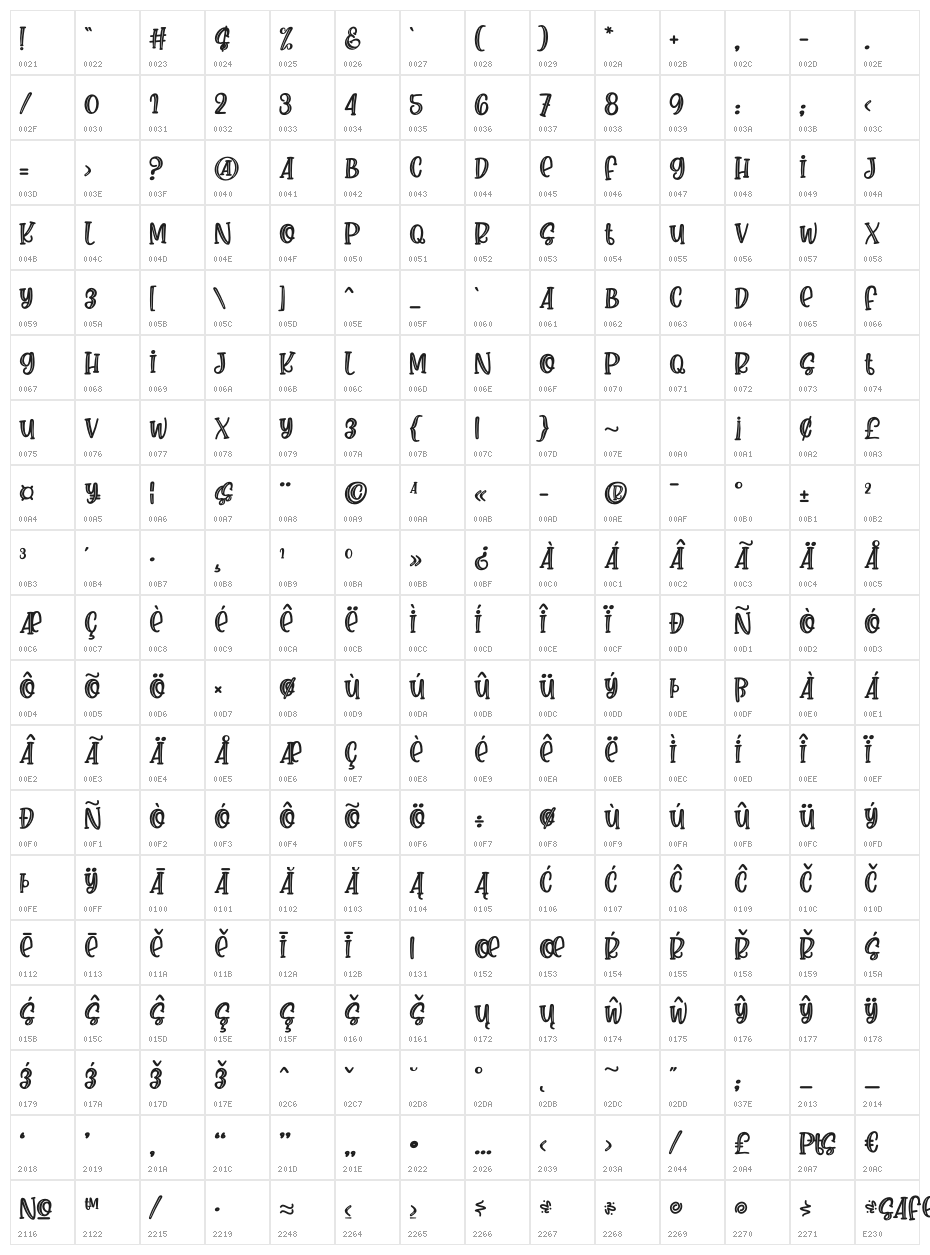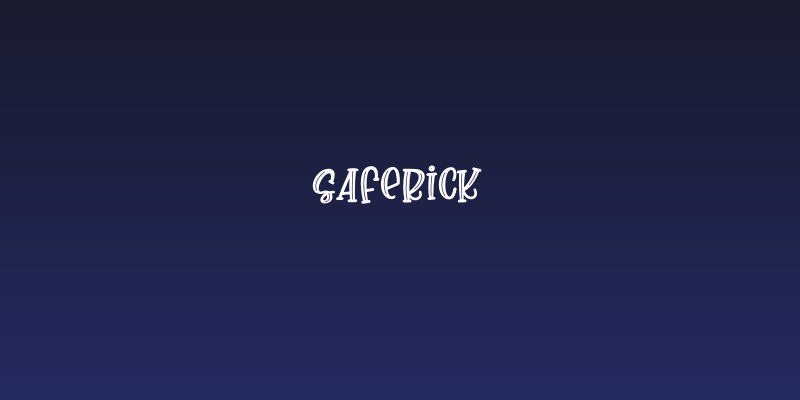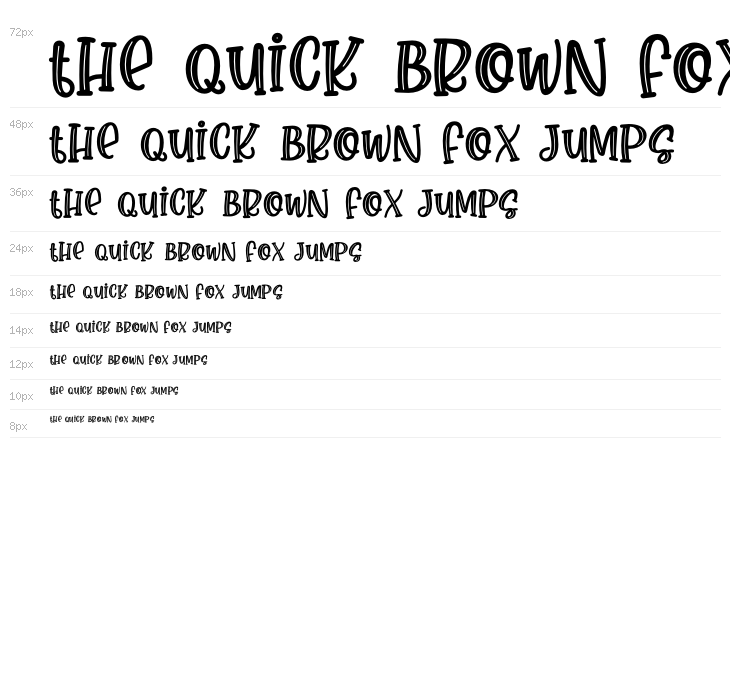
saferick Font
✎ Cartoon
| Anwendungsfall | Logos, Headlines, Posters |
| Vorgeschlagene Projekte | Ideal for children's books, playful branding, greeting cards, and creative posters. |